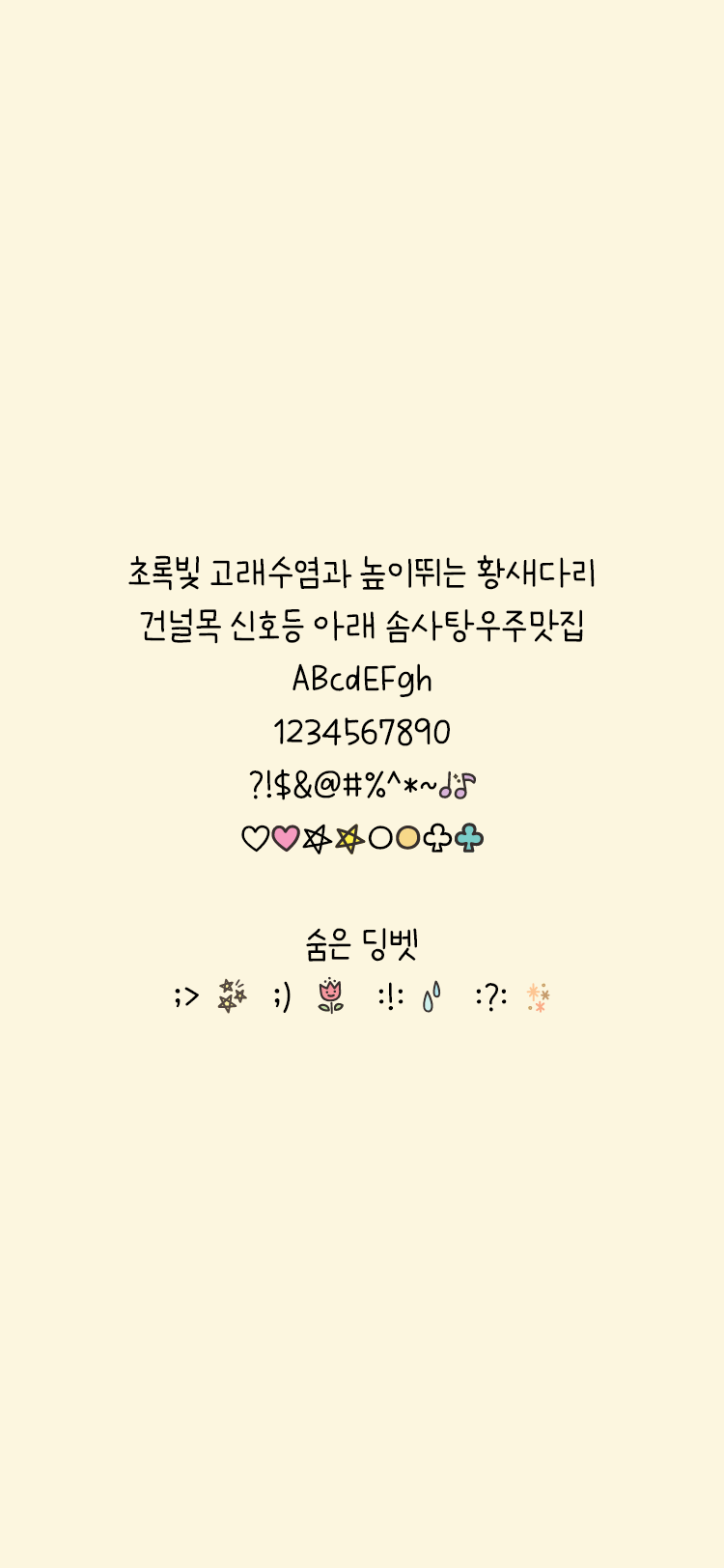
And오늘할일 M
매일 아침,
해야할 일들을 차분히 정리해 적어내려가봐요.
“오늘할일”은 자연스러운 손글씨의 형태를 띈 서체입니다.
*컬러폰트는 일부 앱에선 지원되지 않을 수 있습니다.
*이 폰트는 딩벳을 포함하고 있습니다.
• And오늘할일 M / AndToDolist M